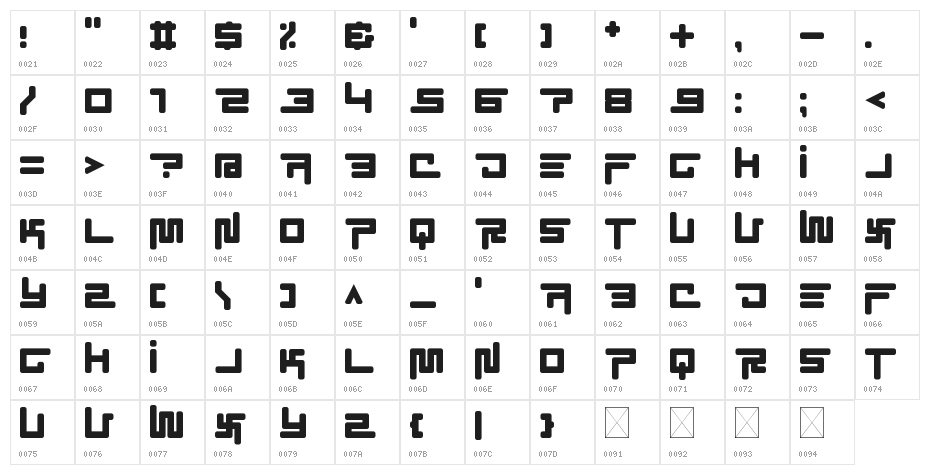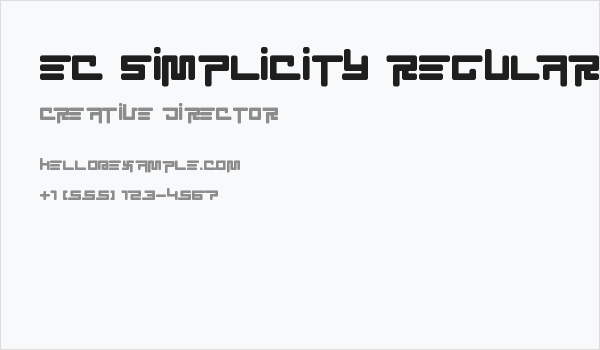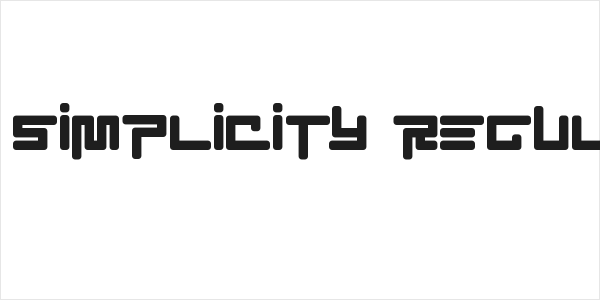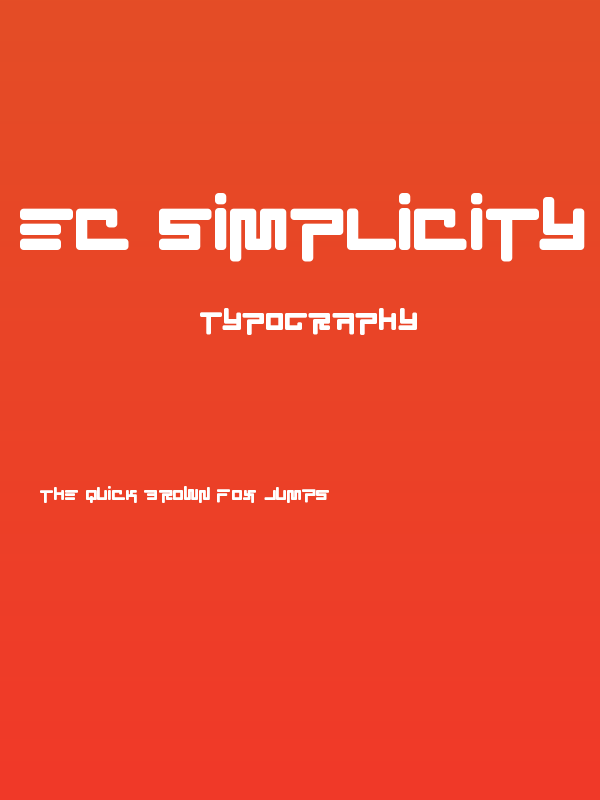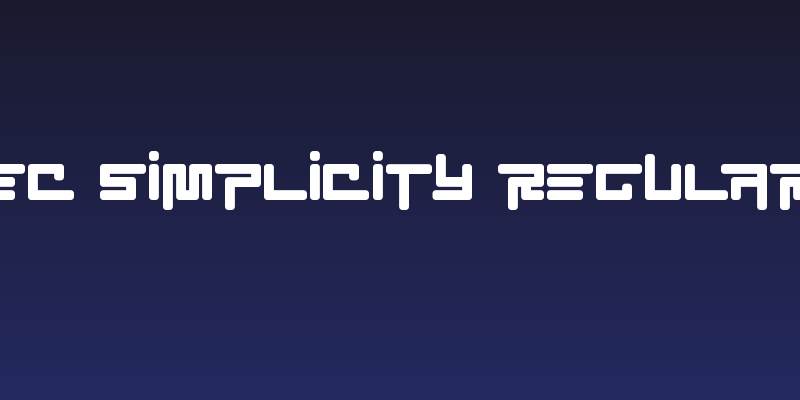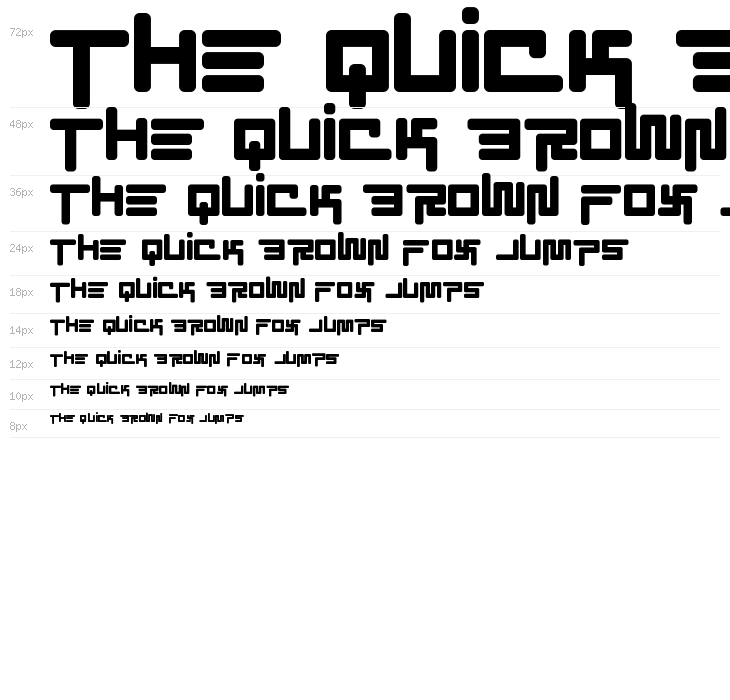
EC SimpliCity Regular Font
| Anwendungsfall | Logos, Headlines, Posters |
| Vorgeschlagene Projekte | Ideal for technology branding, digital interfaces, video game titles, and modern advertising. |